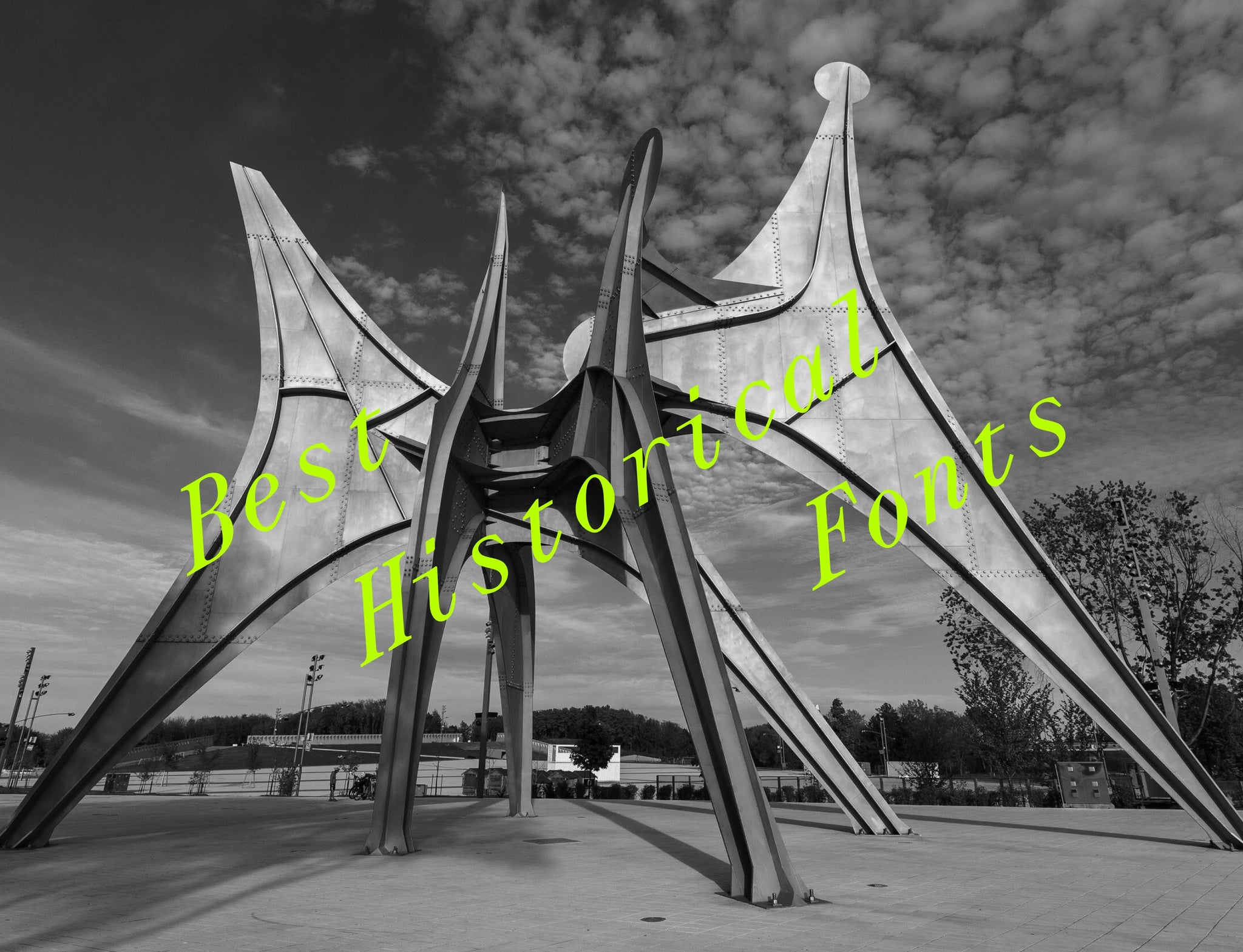
La typographie est une véritable machine à remonter le temps. Chaque lettre est porteuse d'histoire, d'héritage, de récit et de connotation, qu'il s'agisse de l'efficacité ultra-nette des grotesques du milieu du siècle ou de l'élégance ornée d'une police à empattements vieille de plusieurs siècles.
Il est absurde de considérer les polices historiques comme des reliques du passé. Elles sont plus pertinentes que jamais, influençant notre perception et notre interaction avec le design et la typographie contemporains. Et elles sont clairement plus inspirantes que jamais, servant souvent de modèles à leurs homologues contemporains : elles offrent profondeur, caractère et sens du lieu et du temps.
Voici quelques polices d'inspiration historique (disponibles aujourd'hui) qui peuvent ajouter un peu de profondeur supplémentaire à tout ce que vous concevez.
PP Neue Montreal
Certaines polices semblent inévitables, comme si elles avaient toujours été là, attendant d'être utilisées. Neue Montreal en fait partie. Un sans-serif grotesque et indétrônable, offrant un équilibre parfait entre chaleur et fonctionnalité, il explore l'héritage typographique de l'Expo 67 de Montréal tout en s'intégrant parfaitement aux systèmes de design contemporains.
Avec son crénage précis et sa polyvalence de 14 styles (incluant l'italique et le cyrillique), Neue Montreal a déjà marqué la scène du design montréalais, notamment avec le rebranding du club de football montréalais, le FC Montréal. C'est un rappel convivial qu'un bon design, comme une exposition municipale bien planifiée, est à la fois intemporel et évolutif.
PP Editorial New
Il y a une raison à la persistance de certaines esthétiques typographiques : précision, élégance et juste ce qu'il faut de personnalité. Editorial New distille ces qualités dans une police à empattements Narrows, conçue pour les textes longs et affichant une forte présence éditoriale. Inspirée de l'élégance contrastée des imprimés du milieu des années 90, elle passe sans effort des grammages légers, délicats et raffinés, aux courbes plus audacieuses et prononcées des styles plus lourds.
PP Hatton
Certaines polices portent le poids d'un lieu dans leurs lettres (et potentiellement leur héritage à la fois illustre et suspect). Hatton est l'une de ces polices. Hommage au quartier historique londonien de Hatton Garden, centre du commerce du diamant au Royaume-Uni (et de son célèbre braquage), son empattement contrasté, rehaussé d'une touche de charme manuscrit, capture l'esprit de la signalétique et des devantures qui ont longtemps défini ce quartier emblématique.
Méticuleusement mis à jour avec de véritables italiques nouvellement conçues et des proportions raffinées, Hatton apporte une élégance digne mais contemporaine à la fois à l'espace éditorial et à l'espace de marque, offrant un héritage typographique qui semble aussi pertinent aujourd'hui que les trésors brillants auxquels il rend hommage.
PP Editorial Old
Certains disent qu'elle est vieillie à la perfection. Editorial Old est le résultat d'une police à empattements raffinée et contemporaine comme Editorial New, qui s'assouplit et s'use. Inspirée des publicités vintage des années 70 et 80, elle adoucit les courbes précises et les raccords Tights de sa prédécesseure, en introduisant des ligatures décontractées et des détails subtilement érodés. Le résultat est une police qui évoque naturellement la nostalgie, sans pour autant être figée dans le passé.
PP Lettra Mono
Il y a une certaine beauté dans la contrainte. Lettra, une police à empattement fixe, épouse la structure rigide des polices de machine à écrire tout en intégrant les détails fins des illustrations botaniques. Avec ses terminaisons en losange et son fort contraste vertical, Lettra est à la fois précise et expressive – un équilibre rarement atteint dans les polices à empattement fixe.
La police comprend également un jeu de caractères expérimental avec des ligatures ludiques et un « Oo » double chasse inhabituel, ce qui en fait un terrain de jeu pour les typographes et les designers, ainsi qu'un outil performant pour la conception structurée. Lettra prouve que les limites nourrissent la créativité.
PP Nikkei
La typographie peut être un vecteur de narration, et PP Nikkei en est un parfait exemple. Ce système typographique rend hommage à l'histoire de l'immigration japonaise en Amérique, mêlant influences de la signalisation manuscrite des navires, des journaux communautaires Nikkei et des armoiries familiales japonaises traditionnelles.
Avec ses quatre sous-familles et ses 18 styles, Nikkei offre une multitude d'alternatives stylistiques, ce qui en fait un choix polyvalent pour… tout. Avec ses références historiques réfléchies et son exécution contemporaine, Nikkei dé comment une police peut être à la fois un objet fonctionnel et narratif.